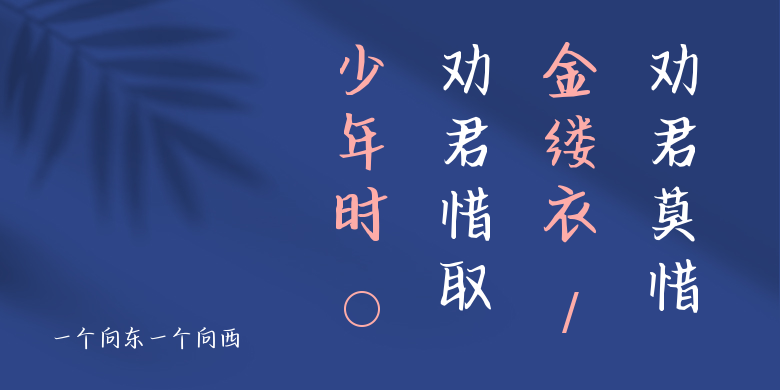
一个向东一个向西
一个向东一个向西,这款字体结构工整、笔画清晰,兼顾美观与易读性,适用于标题、正文、海报、包装、LOGO 等多种场景。字形优雅稳定,风格百搭耐看,适配日常排版与创意设计,让文字呈现更舒适、更具质感。一个向东一个向西一笔一画,皆是细节,以均衡的比例、流畅的线条打造舒适视觉体验,字形端正大气,风格简约现代。无论是商业设计、品牌宣传还是日常排版,都能轻松驾驭,让文字更有格调与力量。一个向东一个向西字体下载。